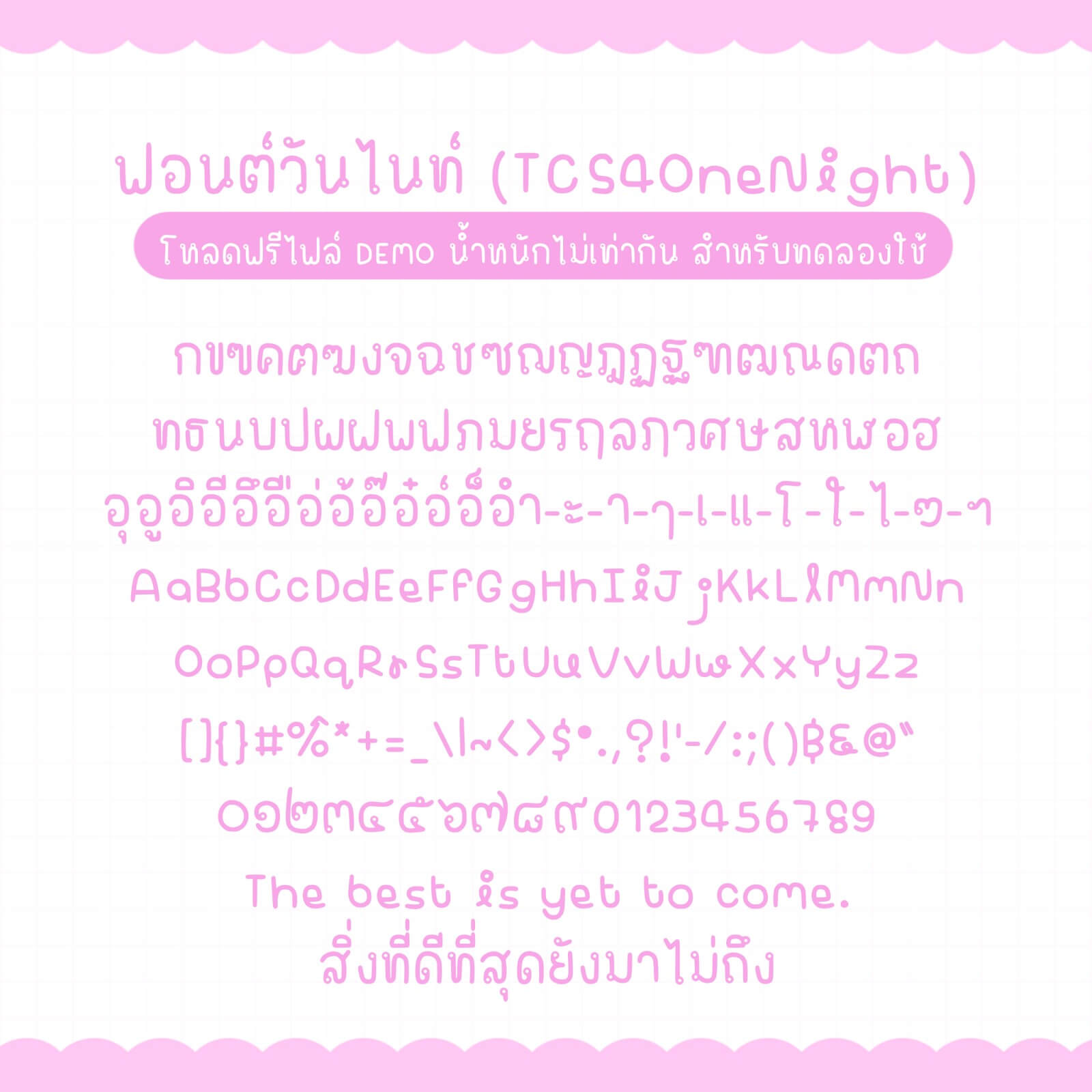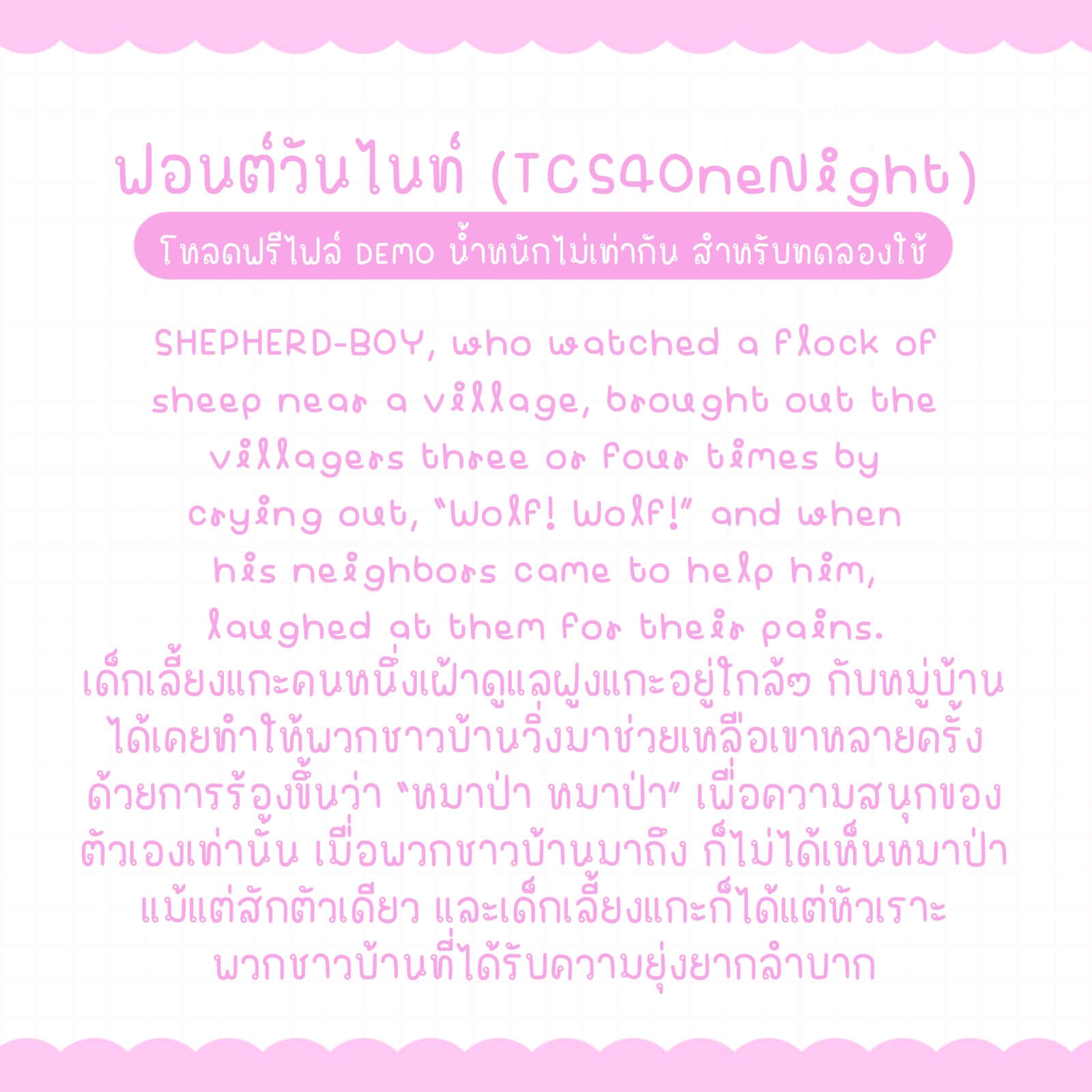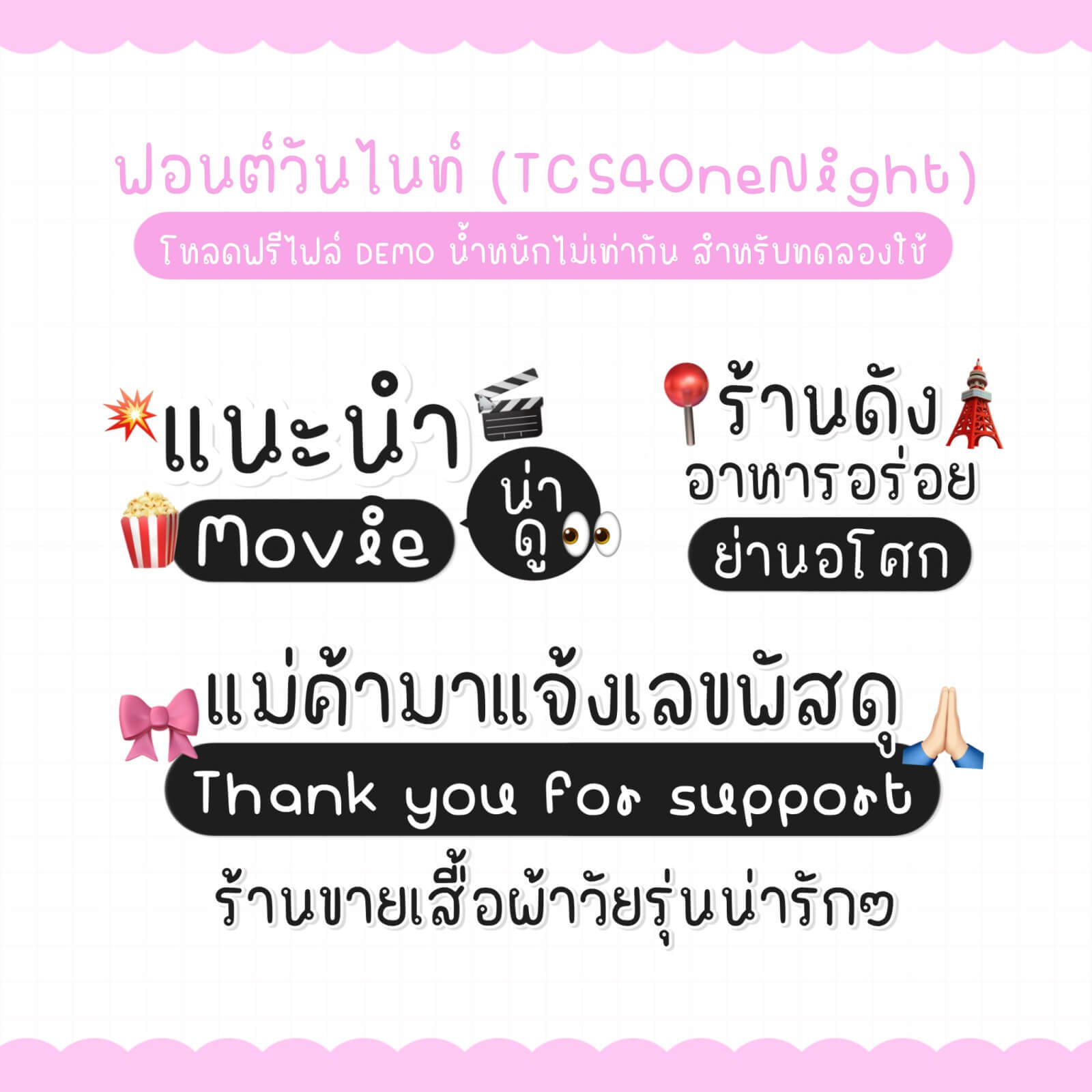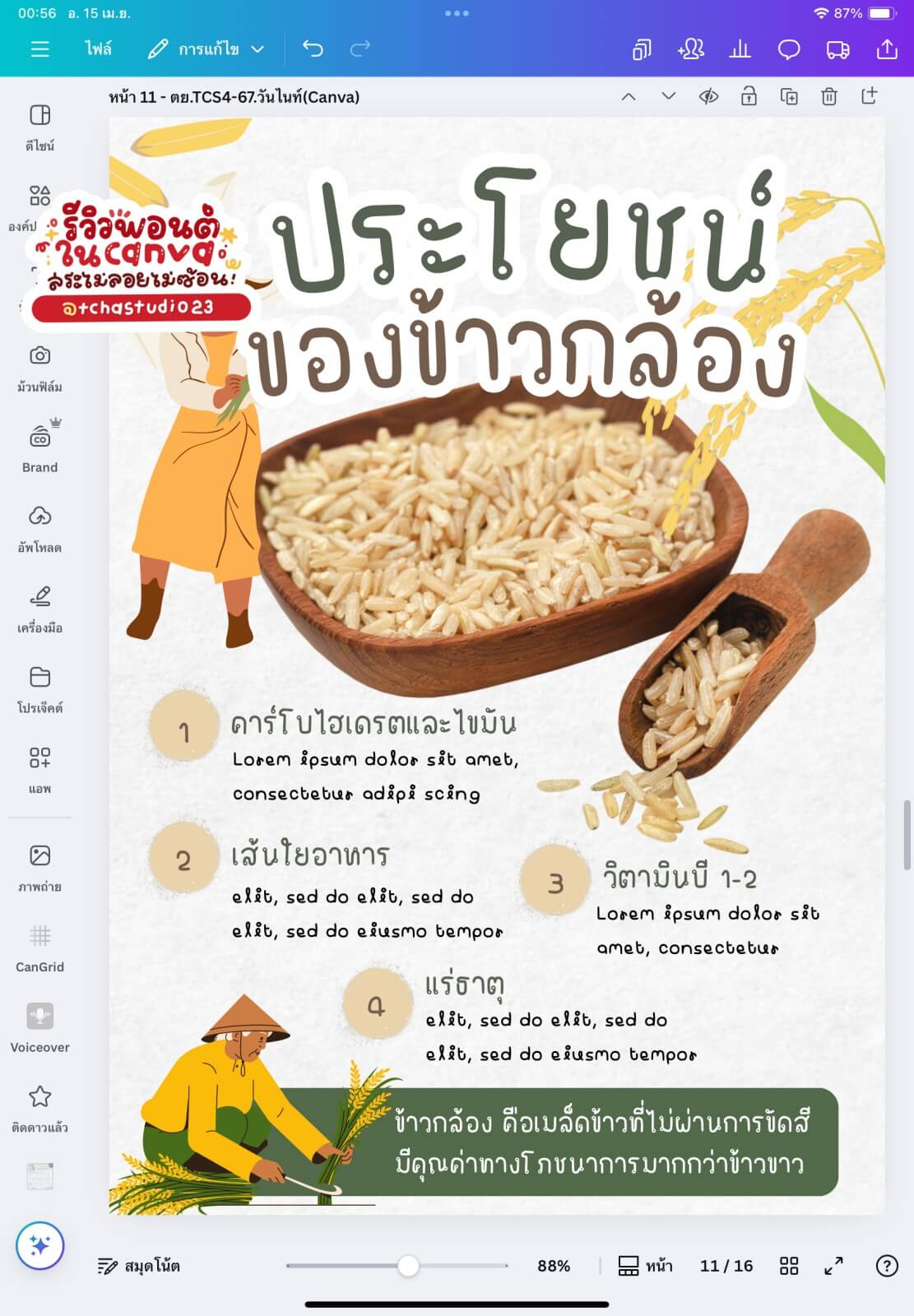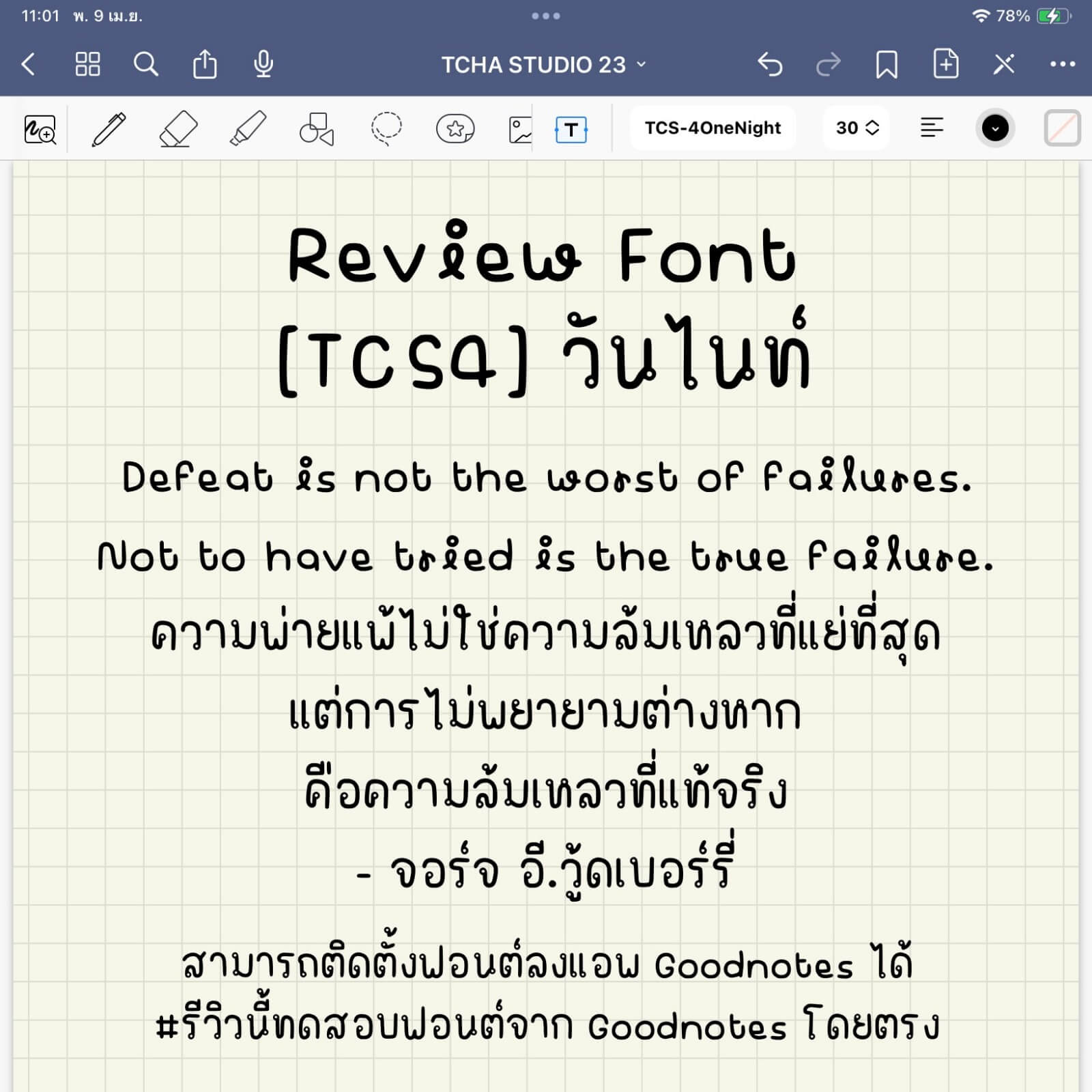
ฟอนต์วันไนท์ (TCS4OneNight)
ฟอนต์วันไนท์ (TCS4OneNight) แนวคล้ายกับ ฟอนต์วันเดย์ แต่วันไนท์ จะมีความผอมแคบ สูงกว่า ตัวหนังสือภาษาอังกฤษมีลูกเล่นกว่าฟอนต์วันเดย์